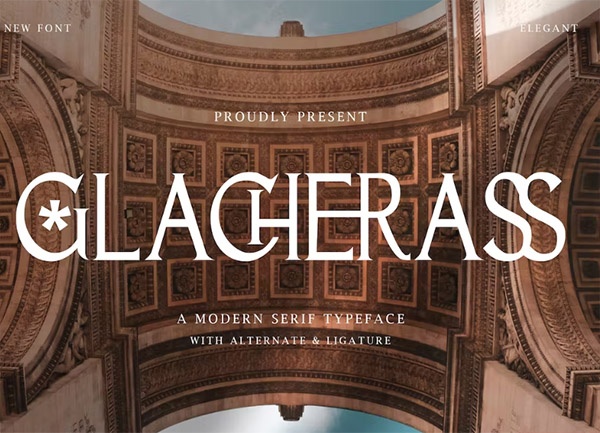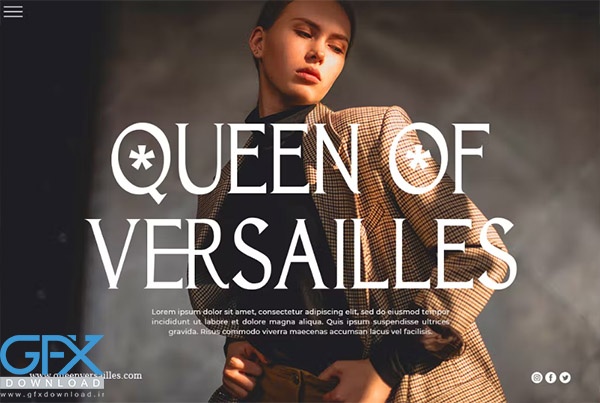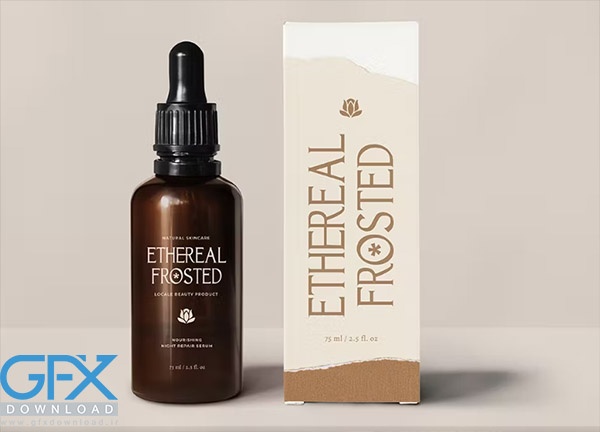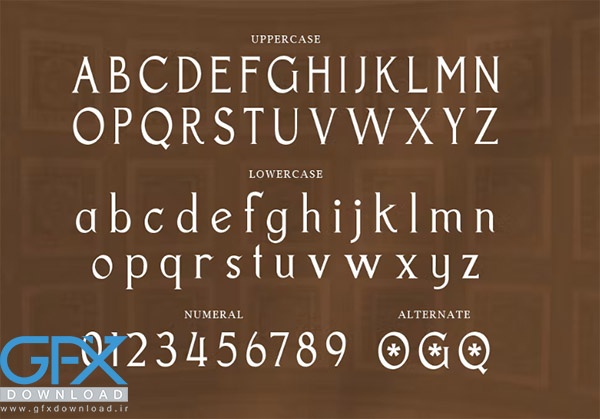
یک فونت عالی سریف مدرن است که تأثیرات سنتی را با زیبایی شناسی معاصر ترکیب می کند. فونت انگلیسی معاصر Glacherass به زیبایی ساخته شده و به راحتی با یک مجموعه بزرگ و باورنکردنی از پروژه ها مطابقت دارد. از این فونت برای دستیابی به ظاهری ظریف و در عین حال ظریف و حداکثر تطبیق پذیری استفاده کنید.
این فونت معاصر شامل حروف بزرگ – کوچک – نمادها و علائم نقطه گذاری – اعداد – لیگاتور – جایگزین – پشتیبانی چند زبانه می باشد. فایل شامل: گلاچراس (OTF، TTF، WOFF، WOFF2) می باشد.